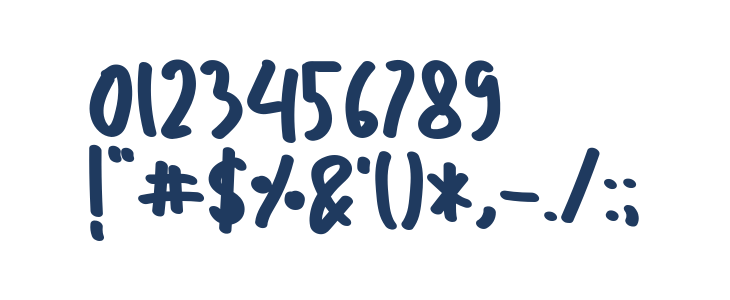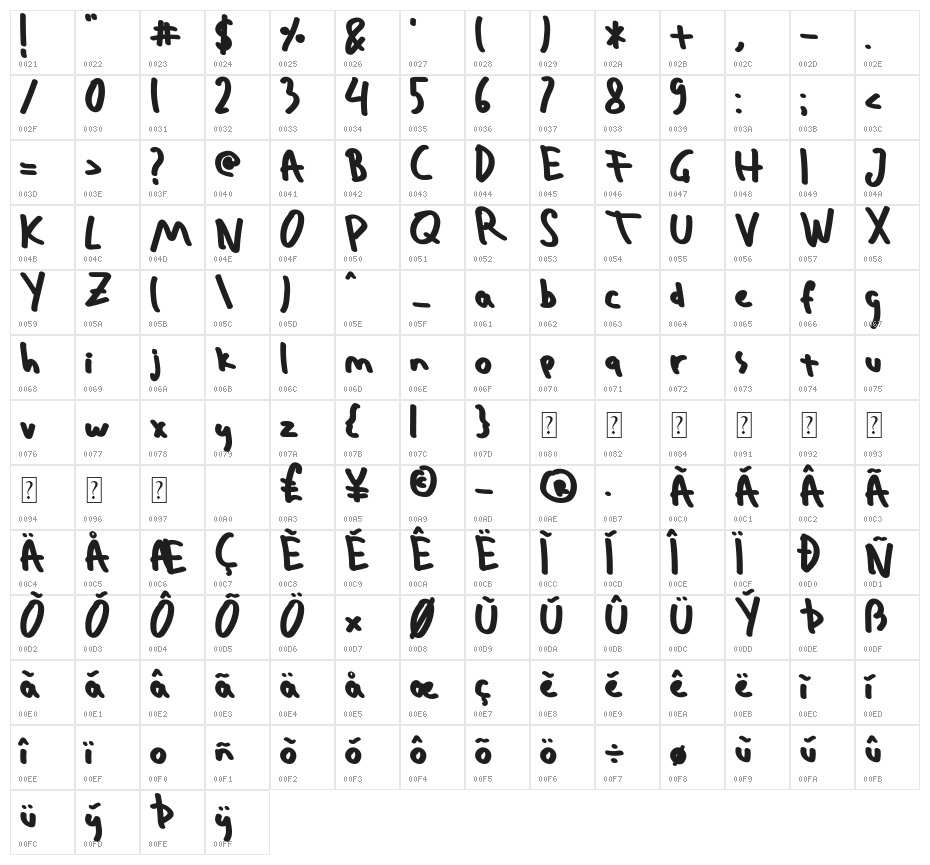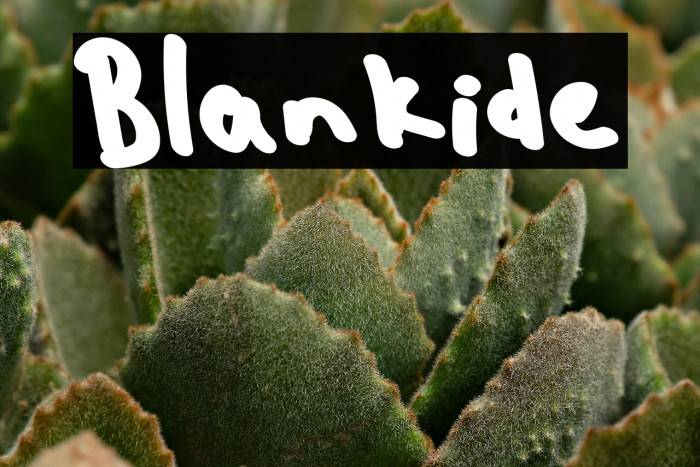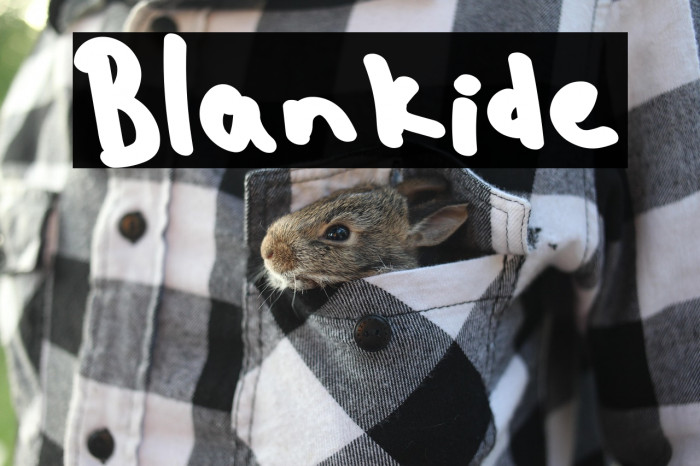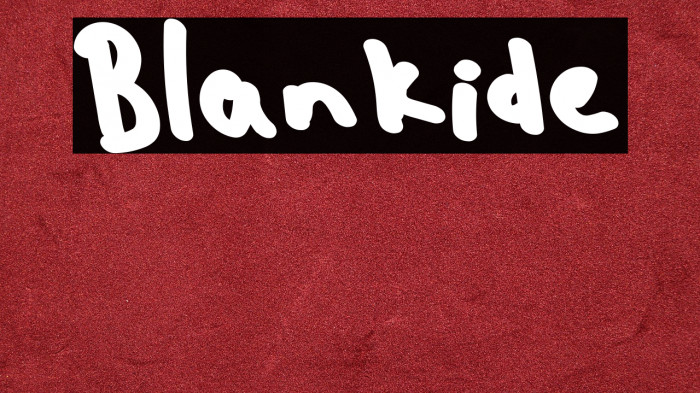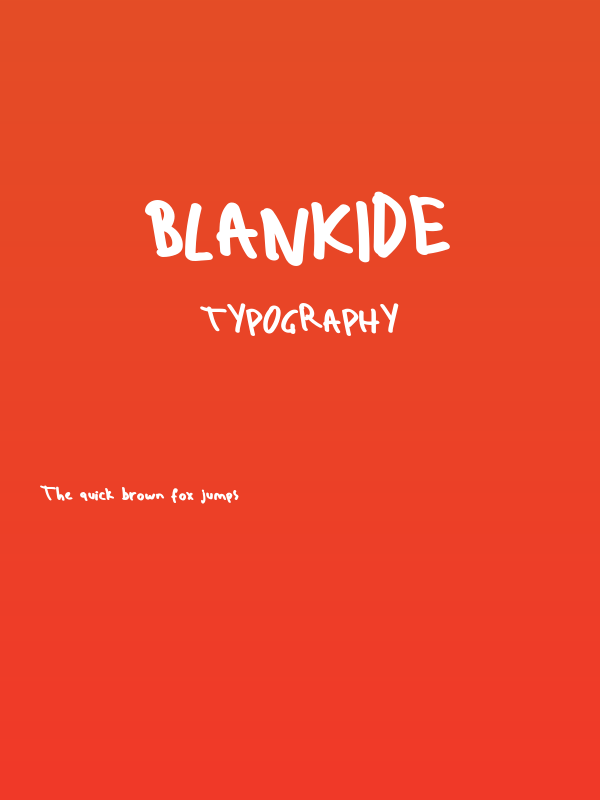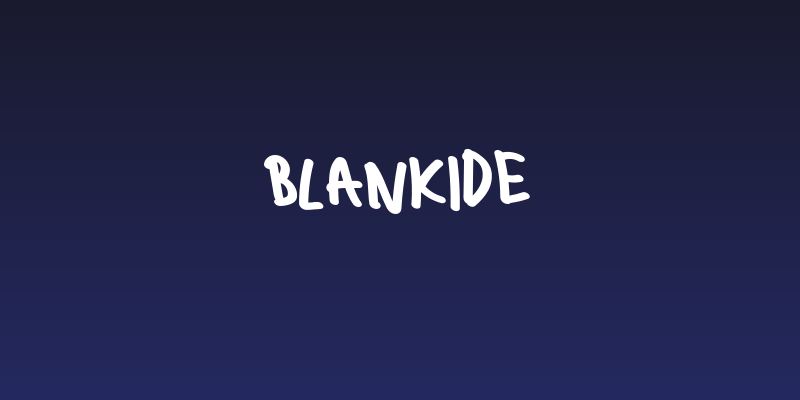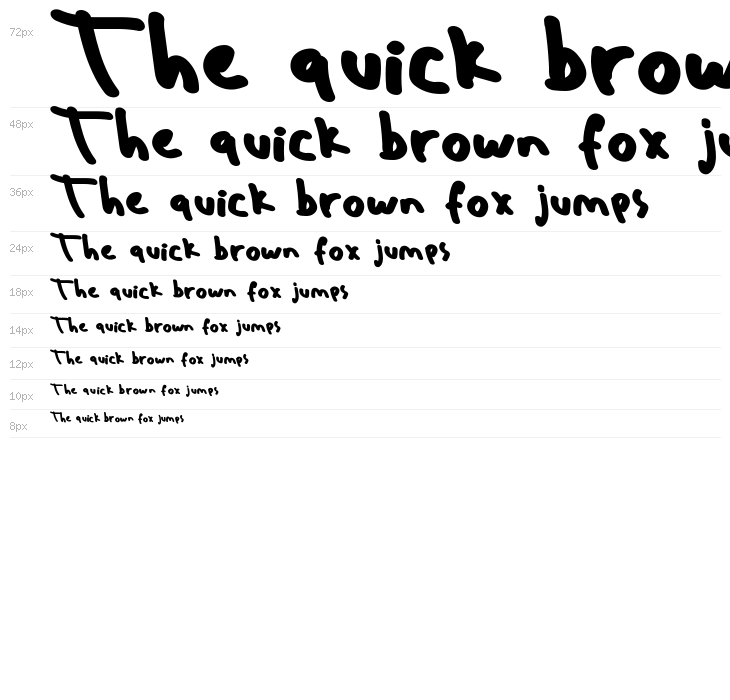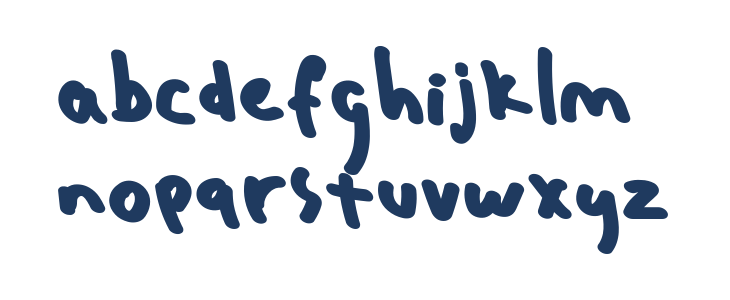
Blankide Font
| Gesamtstil | Casual, Playful |
| Vorgeschlagene Projekte | Great for children's books, greeting cards, posters, and creative branding projects. |